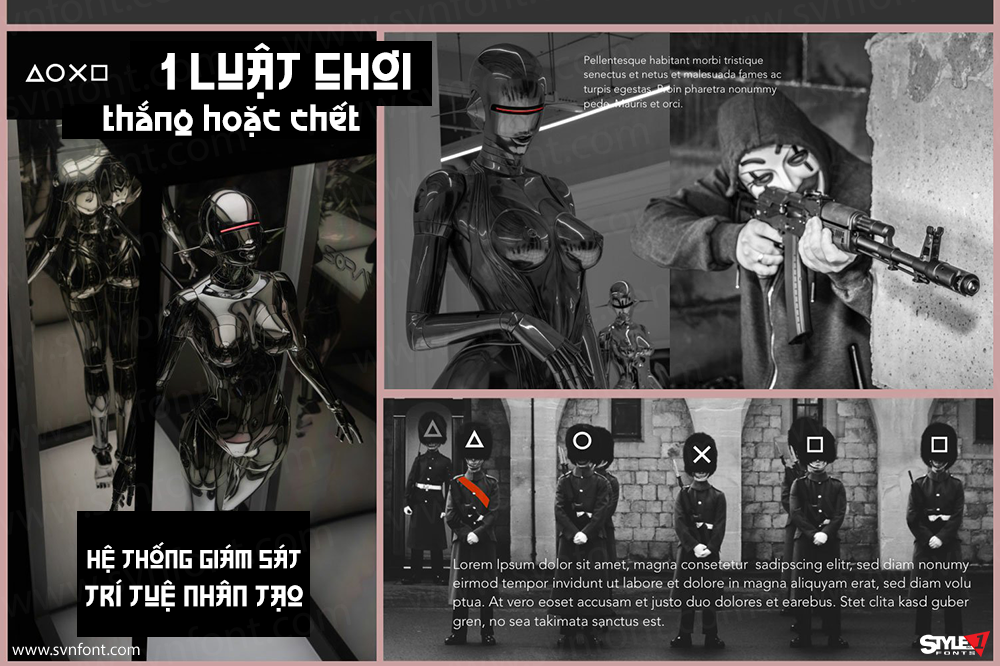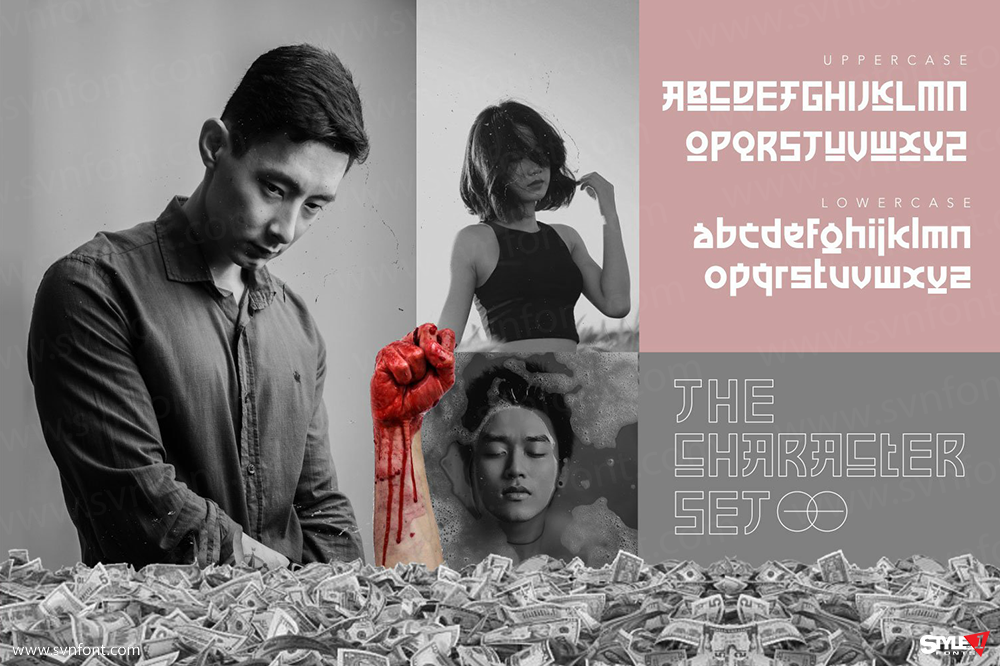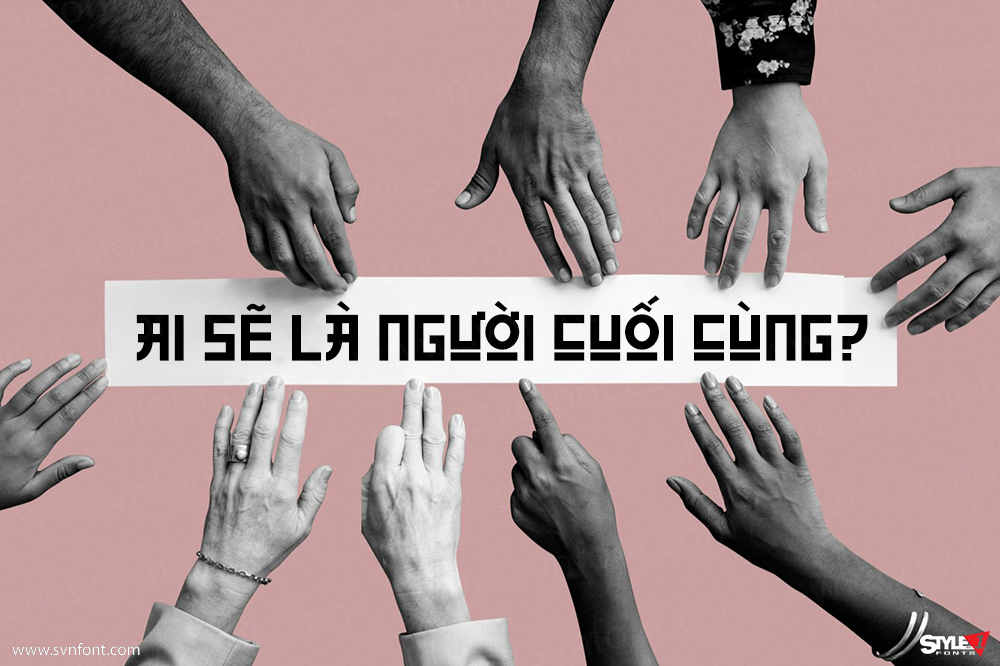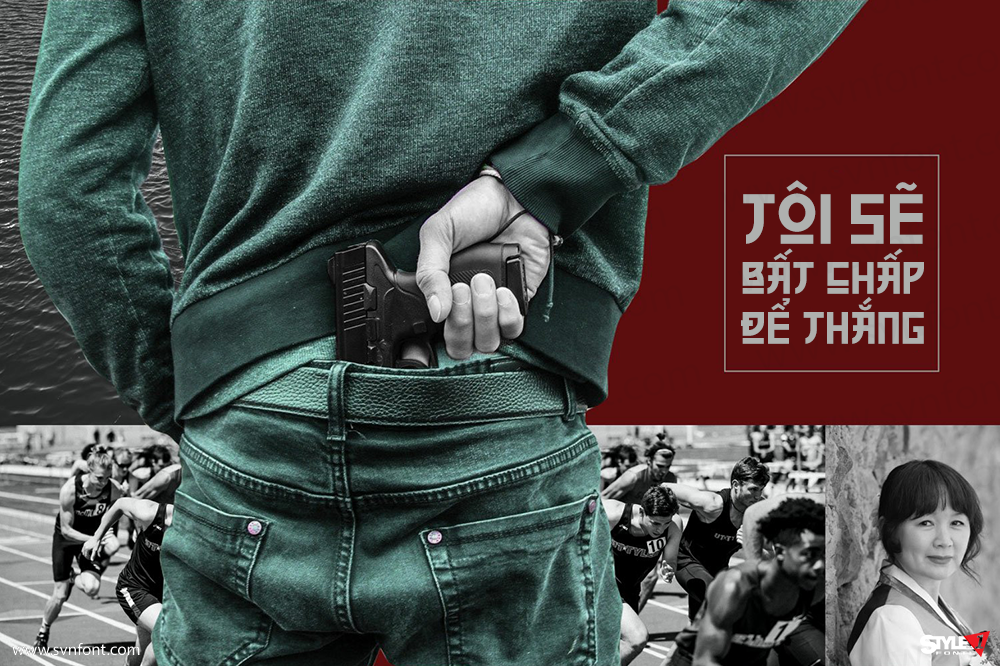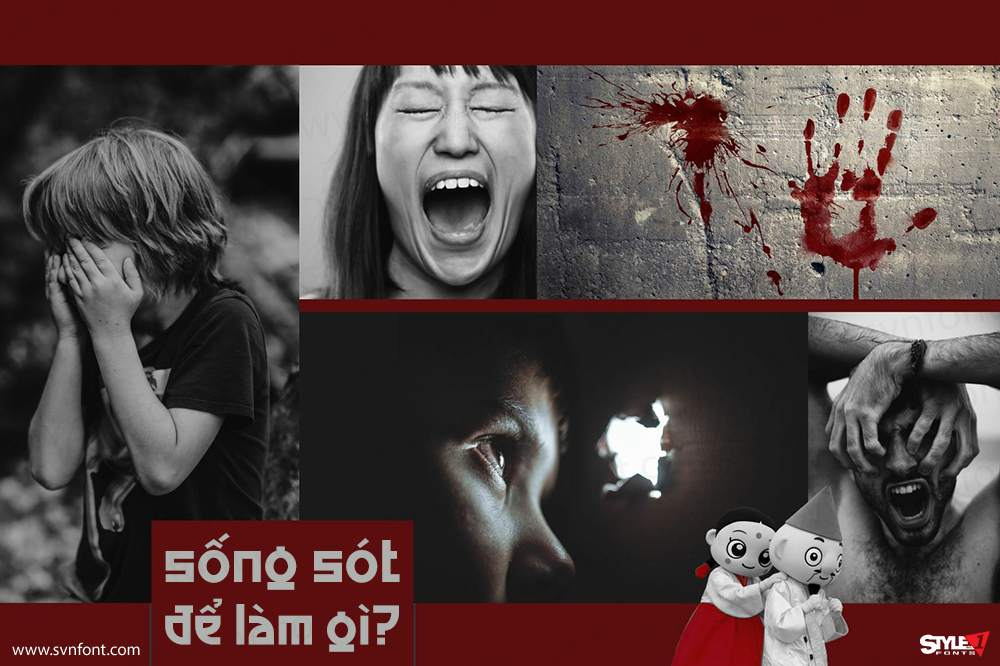
Lấy cảm hứng từ các bộ phim truyền hình Hàn Quốc nổi tiếng, Money Game là một lựa chọn tuyệt vời cho các thiết kế chủ đề Hàn Quốc của bạn. Nó hoàn hảo cho áp phích phim, thiệp chúc mừng, nội dung mạng xã hội, video YouTube, thậm chí là thiết kế logo, v.v. Font này trông giống như chữ cái tiếng Hàn, vì vậy bạn sẽ cảm nhận được tinh thần Hàn Quốc.